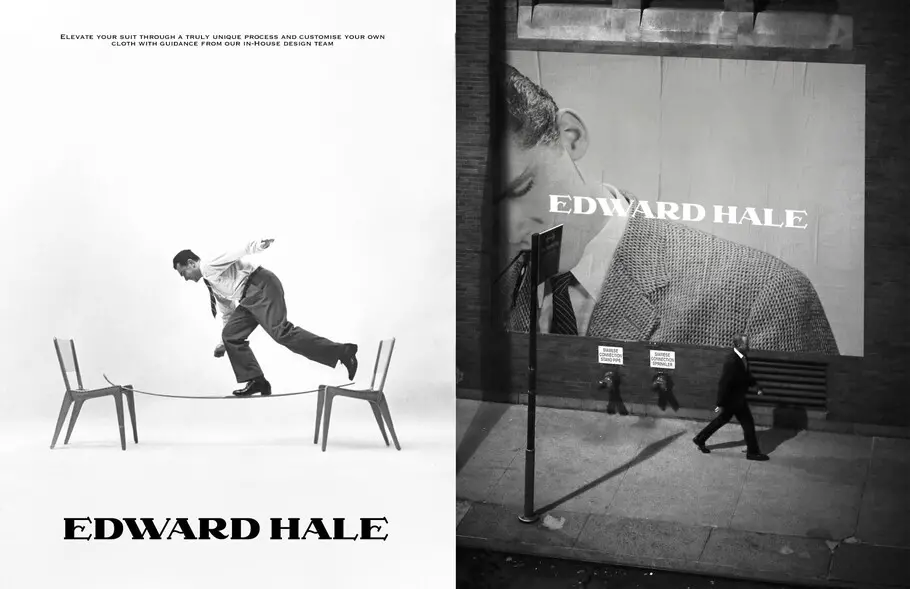
Tudo o que é antigo é novo de novo: um olhar mais profundo sobre a nostalgia no design.
Como podemos reviver elementos de design lúdicos e reconfortantes do passado, sem ignorar verdades dolorosas sobre cada época?
A nostalgia, pensada para ajudar as pessoas a lidar com tempos de crise, está tendo um momento em designs de todos os tipos. Exploramos o que está impulsionando a tendência e algumas das complexidades inerentes ao reviver elementos históricos do design.
Nos últimos dois anos, a nostalgia começou a se infiltrar em muitas facetas da vida cotidiana – moda e móveis, identidades de marca e até mesmo a música que ouvimos. Durante os dois anos mais incertos e perturbadores que a maioria de nós já viveu, vimos marcas e designers buscarem uma sensação de conforto reinventando o familiar. Cientificamente, faz sentido, pois os psicólogos descobriram que relembrar pode ajudar as pessoas a lidar com as crises.
Assim como escolher antiguidades, os designers também adoram buscar inspiração em logotipos, livros, pôsteres e livros históricos e prestar homenagem a esses designs. Quantas fontes foram inspiradas nas letras de um livro antigo descoberto em uma livraria ou de um cartão postal adquirido em uma liquidação? É uma forma de celebrar ícones ou selecionar um estilo único – seja em um logotipo, no seu armário ou na sua casa.
Até mesmo nosso mais recente lançamento de estúdio, uma serifa contemporânea intitulada Cotford, do Diretor Criativo de Tipografia Tom Foley, carrega um toque nostálgico. “Cotford reflete uma experiência que muitas pessoas tiveram durante o pico dos confinamentos do ano passado: um anseio por conforto familiar e um pouco de calor em meio à incerteza.”
A emoção da descoberta.
Fora da fonte e do design gráfico, os estilos vintage ganharam popularidade em móveis, decoração e moda. O ritual de descobrir um pedaço raro da história e dar-lhe uma nova vida no mundo moderno ofereceu alívio durante a pandemia e cresceu através de novos canais como o Instagram e sites de revenda de moda como o Depop.
As tendências da moda sempre surgiram em ciclos, mas, de acordo com a ThredUp, uma loja de revenda online, a economia cresceu recentemente e se tornou uma indústria de $36 bilhões que deverá ofuscar a fast fashion até 2025. Um maior foco na sustentabilidade fez com que multidões de consumidores cada vez mais jovens se voltassem para a consignação, em vez de apoiarem a fast fashion. A pandemia também causou problemas na cadeia de abastecimento em quase todos os setores, e alguns clientes preferem a gratificação instantânea da economia a esperar pelo atraso no envio de novos itens.
A busca por achados vintage também se estende ao mundo vivido, como o fotógrafo Tyler Haughey compartilhou em nosso podcast. Seu trabalho se concentra em certos significantes, como sinalização ou decoração antiga, para explorar como esses itens podem ancorar memórias ou experiências em nossas mentes. “As memórias começam sendo muito familiares, recentes e tangíveis”, disse Haughey, “e então, à medida que você se afasta cada vez mais, elas se tornam estranhas e assumem esse elemento fantástico. Acho que a natureza da memória é que ela se torna cada vez menos específica com o passar do tempo.”
Todos esses elementos, sejam fontes borbulhantes no estilo dos anos 70, fotos nebulosas de cidades litorâneas antigas, jeans baratos ou móveis antigos, podem servir como veículos para contar histórias e reviver o passado. Em nosso Relatório de tendências de 2021, identificamos pela primeira vez nossa tendência de fonte serifada “soft-serve” depois de notar a aparência de serifas clássicas, aconchegantes e fortemente nostálgicas influenciadas por Cooper Black em rebrands para Chobani (InHouse), MailChimp (Collins), Meridian (BulletProof ), Dunkin e Burger King (JKR). Depois de um ano implacável, a tendência manteve-se forte, aparecendo através de formatos de letras com traços divertidos, serifas grossas, letras peculiares e esquemas de cores vibrantes.
Celebrando a diversidade na história.
O que fica complicado, porém, é separar essa apreciação pelos elementos do design patrimonial dos contextos sociais às vezes desagradáveis em que nasceram. “Toda essa ideia de nostalgia e óculos cor de rosa nos deixa propensos a escolher a dedo, ignorando o sexismo, o racismo e a desigualdade social, e dizendo: ‘Bem, houve um tempo em que os homens brancos podiam jogar beisebol!”” O Diretor Criativo da Monotype, Charles Nix, destacou em uma entrevista à Print Mag sobre o ressurgimento do design de uniformes esportivos retrô.
Então, como podemos reviver elementos de design lúdicos e reconfortantes do passado, sem ignorar verdades dolorosas sobre cada época?
Para voltar à fonte, vejamos o trabalho que Tré Seals, proprietário e fundador da Vocal Type, está fazendo ao usar fontes como meio de contar histórias. Todas as fontes do Vocal são derivadas de eventos históricos, como marchas e protestos, e têm nomes de proeminentes defensores da justiça social, incluindo Marsha P. Johnson, Martin Luther King e Bayard Rustin.
Como designer negro que não se via representado na indústria, Seals falou sobre a falta de diversidade no design e como isso moldou sua carreira.
“Em março de 2016, enquanto procurava fontes sem rumo enquanto criava outra identidade para outra agência imobiliária, fiquei muito entediado”, disse Seals em uma entrevista no It’s Nice That, “Tudo o que vi, por mais bonito que fosse, parecia sempre igual. Você poderia argumentar que é porque somos obcecados por grades e perfeição, mas a verdade é que não havia cultura, nem caráter – apenas monotonia e estereótipos. Embora o design seja minha paixão, comecei a me perguntar se havia escolhido a carreira errada.”